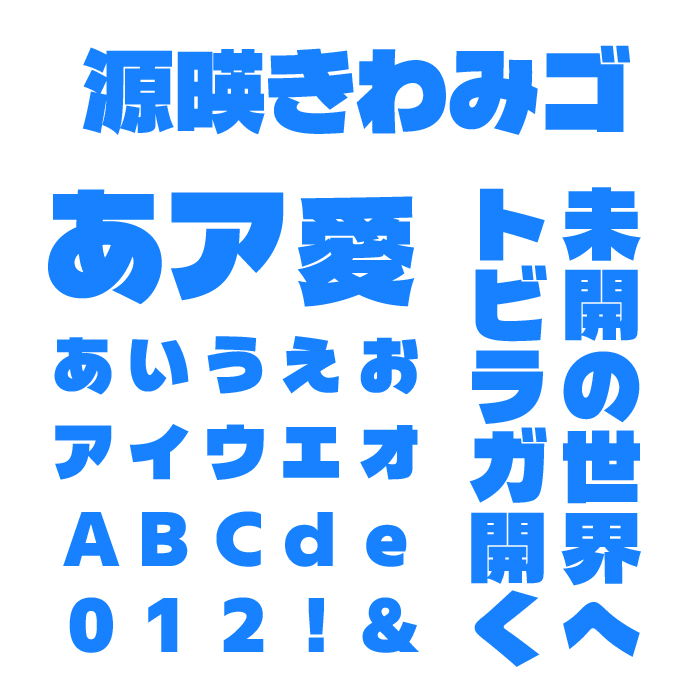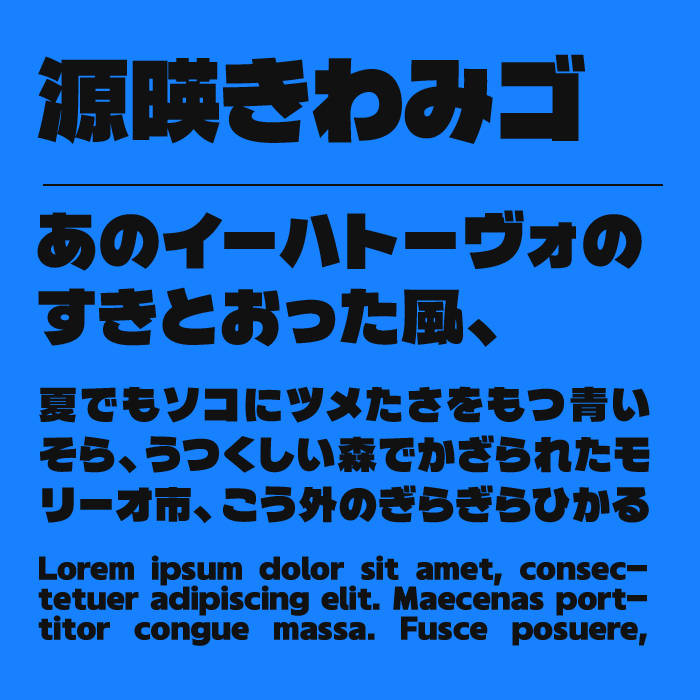
源暎きわみゴフォントは、直線的でかっちりとした骨格を持ちながら、少しの丸みを加えることで親しみやすさも感じさせるデラゴシックフォントの派生ゴシック体です。
オリジナルで制作されたかな文字はは、文字の重心がやや低めで、落ち着いた雰囲気があり、安心感のある印象を与えます。
太さはしっかりありながらも詰まりすぎず、文字間のバランスも良好です。硬派なデザインにも使いやすく、チラシやポスター、雑誌の見出しなど幅広い場面で活用できます。信頼感と視認性の両立を求める方にぴったりなフォントです。
収録文字は、漢字・ひらがな・カタカナ・アルファベット・数字・記号が収録。